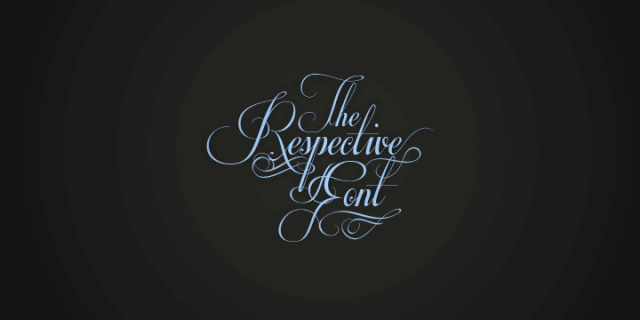
Como me gusta esta entrada y como me gusta este dia!!! Como cada viernes os traigo la tipografía que más me ha gustado de la semana. La de hoy es una tipografía caligráfica finísima. Trabajada al detalle. Es del diseñador sueco Måns Grebäck. OJO CON LA LICENCIA, es una tipografía cuya licencia estándar es para uso SÓLO PERSONAL. Al pie de la entrada os dejo el link tanto de la descarga de la tipografía para uso personal como el link para comprar la licencia comercial. El precio de la licencia completa son 59$ muy bien ganados como podéis ver. Espero que os guste y recordad que los like y los follow ayudan mucho así que visitadnos en Twitter y Facebook. También nos podéis encontrar en Flipboard buscando nuestra revista El Arquitecto de Ilusiones.